Шрифт для надписей на машиностроительных чертежах. Форма букв русского алфавита и арабских цифр
ШРИФТ ДЛЯ НАДПИСЕЙ НА
МАШИНОСТРОИТЕЛЬНЫХ ЧЕРТЕЖАХ
ФОРМА БУКВ РУССКОГО АЛФАВИТА И АРАБСКИХ ЦИФР
Прописные буквы
К первой группе относятся буквы Г, Е, Н, П, Т, Ц, Ш, Щ,
образованные из одних прямолинейных элементов,
расположенных горизонтально и с наклоном.
Ко второй группе относятся буквы, Ж, И, Й, К, М, X,
состоящие из наклонных и диагональных элементов.
К третьей группе относятся буквы А, Д, Л, состоящие из
горизонтальных, наклонных и диагональных элементов.
К четвертой группе относятся буквы Б, В, Р, У, Ч, Ъ, Ы,
Ь, Я, образованные из горизонтальных, наклонных,
диагональных и криволинейных элементов.
К пятой группе относятся буквы 3, О, С, Ф, Э, Ю,
состоящие в основном из криволинейных элементов.
Строчные буквы
К первой группе относятся буквы н, к, ж, м, л, х, состоящие
из горизонтальных, наклонных и диагональных элементов.
Ко второй группе относятся буквы ч, ъ, ы, ь, я, состоящие
из горизонтальных, наклонных, диагональных и
криволинейных элементов, конструкция которых также
ничем не отличается от конструкции одноименных
прописных букв.
К третьей группе относятся буквы а, б, в, д, е, о, р, с, э, ю.
Все буквы этой группы строятся на основе буквы о и
содержат в себе криволинейные элементы.
К четвертой группе относятся буквы и й, п, т, у, ф, ц, ш,
щ, состоящие из прямолинейных и криволинейных
элементов.
К пятой группе относятся буквы г и з, состоящие из криволинейных элементов. Они строятся на основе цифры 8.
По ширине прописные и строчные буквы можно
разделить на нормальные, расширенные и
широкие.
К широким буквам относятся прописные Д, Ж, Ф, Ш, Щ,
Ы, Ю и строчные ж, м, ф, щ, ъ, ы, ю.
К расширенным буквам относятся только прописные М и Ъ.
Все остальные прописные и строчные буквы относятся к
нормальным.
По высоте исключение составляют шесть строчных
букв б, в, д, р, у, ф, которые условимся называть высокими.
Основные размеры чертежного шрифта
Размер шрифта определяется высотой h прописных
(заглавных) букв в миллиметрах, которая является
основной
его
характеристикой.
Государственный стандарт 3454—59 «Шрифты
чертежные» устанавливает следующие размеры
шрифта: 2,5; 3,5; 5; 7; 10; 14. При этом шрифт
размера 2,5 имеет только прописные буквы и
цифры.
Высота строчных (малых) букв каждого размера
шрифта, кроме шрифта 2,5, составляет приблизительно
5/7 от высоты, прописной (заглавной) буквы
На рис. 2 приведено сопоставление размеров прописных и строчных букв различных
размеров шрифта.
Таким образом, в указанном ряде размеров шрифта каждый последующий размер
составляет приблизительно 5/7 от высоты предыдущего, а строчные буквы, будучи равными
5/7 от высоты прописных букв, соответствуют следующему меньшему размеру шрифта.
Исключение составляют шесть строчных букв б, в, д, р, у, ф , которые имеют такую же
высоту, как и прописные (заглавные).
При рассмотрении форм букв русского алфавита чертежного
шрифта мы установили, что прописные буквы по ширине
можно разделить на нормальные, расширенные и широкие, а
строчные — на нормальные и широкие.
Ширина b нормальных прописных букв равна
приблизительно 5/7 от высоты шрифта (рис. 3), ширина b1
расширенных прописных букв (М, Ъ) —6/7 от высоты шрифта,
а ширина b1 широких прописных букв (Д, Ж, Ф, Ш, Щ, Ы, Ю)
равна высоте шрифта (рис. 4).
Ширина Ь3 нормальных строчных букв составляет приблизительно 3/7 от высоты прописной буквы (рис. 3), а широких
строчных букв bi (ж, м, т, ф, ш, щ, ъ, ы, ю) ■— 4/7 от высоты
прописной буквы (рис. 4).
Толщина линий обводки прописных, строчных букв и цифр
должна быть везде одинакова. ГОСТ 3454—59 установлено,
что
толщина линий обводки прописных букс и цифр b6 должна равняться 1/7 от
их высоты, толщина линий обводки строчных букв b7—1/10 от высоты
прописной буквы, что практически составляет примерно 1/7 от высоты
строчной буквы (рис.
3,4). При Выполнении надписи строчными буквами
толщина линий обводки прописных (заглавных) букв должна быть такая
же, как и строчных, т. е. 1/10 от высоты прописной буквы (рис. 5).
Все размеры элементов букв и цифр зависят от высоты (размера) шрифта,
а
их
соотношение
является
кратным
1/7.
Буквы и цифры чертежного шрифта должны быть написаны с наклоном
75° к основанию строки. Такой наклон шрифта соответствует обычной
манере письма. Кроме того, в рукописных шрифтах легче достигнуть
одинакового наклона элементов букв и цифр, чем их строгой
вертикальности. Наклон шрифта облегчает выполнение надписей и
несколько скрадывает недостатки, неизбежные при выполнении надписей
от руки. Практическим преимуществом такого наклона является удобное
получение угла 75° с помощью рейсшины и двух обычных чертежных
угольников с острыми углами 45 и 30°, которые при прикладывании друг
к
другу
дают
в
сумме
требуемый
угол
(рис.
6).
Угол, приблизительно равный 75°, можно также получить построением
уклона с отношением сторон 1 : 4, что соответствует
наклону гипотенузы прямоугольного треугольника, горизонтальный катет
которого равен единице, а вертикальный — четырем единицам.
Стандартом в особых случаях допускается применение и прямого (без
наклона) шрифта при условии сохранения установленных требований в
отношении
начертания
и
размеров
букв
Вспомогательная сетка для чертежа прописных букв
На рис. 20 показаны конструктивные особенности и соотношения между элементами букв при
вписывании их в размерные рамки (сетку).
Буквы, второй группы Ж, И, И, К, М, X (рис. 21) образованы из наклонных и диагональных
элементов.
Особое внимание следует уделять выполнению диагональных элементов буквах К, Ж
и М.
Нижний наклонный элемент буквы К располагается по диагонали параллелограмма,
а верхний — из правой вершины параллелограмма в точку, расположенную на его
левой стороне на расстоянии 2/7 h от нижней линии строки.
Прямой шрифт
Обводка надписей
Шрифты для архитектурных
чертежей
Шрифт зодчего
Художественные шрифты
Как правильно их рисовать (+ разные стили)
Главная » Надписи цифр: Как правильно их рисовать
Автор: Тимо Страус
Страстный художник леттеринга, дизайнер и основатель lettering.org […]
Of Конечно, вы также можете использовать цифры и цифры в своих надписях от руки! К сожалению, в большинстве руководств им не уделяется много внимания.
Поэтому в этой статье я хотел бы показать вам базовый рисунок штриха для написания цифр от руки и вдохновить вас некоторыми стилями.
Кроме того, я покажу вам числа, которые вы, вероятно, никогда раньше не замечали сознательно…
Содержание
Основные шаблоны
Для записи чисел от нуля до девяти (обычным способом) существует типичная последовательность ударов. Так создаются отдельные цифры, которые можно сложить вместе, чтобы сформировать числа.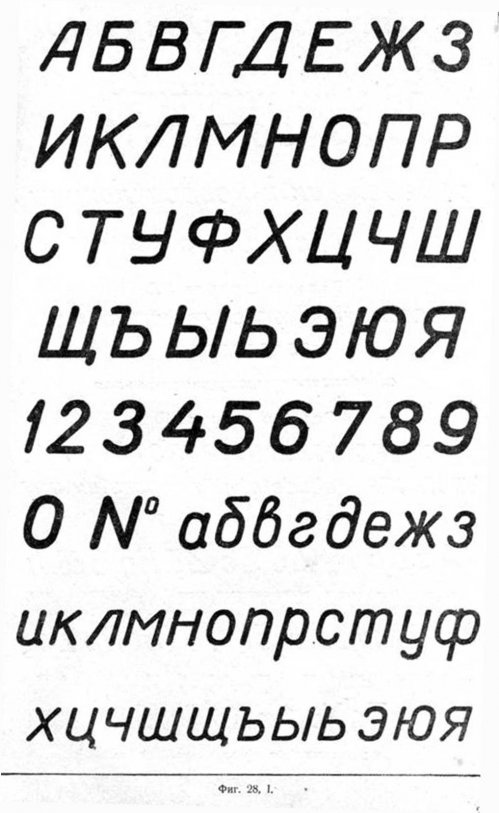
На следующем фото я выделил эти строки простым шрифтом:
Подход очень похож на тот, что я выучил в школе.
Отдельные движения точно согласованы друг с другом для создания наилучшего возможного потока письма. Только с «9» я выбрал другое управление линиями, которое поможет вам в написании кистью.
Написание чисел с помощью кистей
Типичные контрасты ширины линий, которые делают надписи кистью такими особенными, также можно применить к цифрам (для этого вам понадобится кисть).
Чтобы работать в нужных местах с большим и небольшим нажимом, важно знать основные штрихи линии.
Потому что, если вы уже можете правильно рисовать отдельные штрихи, все, что вам нужно сделать сейчас, это применить принцип письма кистью к штрихам:
- Штрихи от сверху донизу выполняются с большим давлением , создается толстая линия
- Штрихи от снизу вверх выполняются с небольшим нажимом , в результате получается тонкая линия
Цифры, написанные от руки, подчиняются тем же правилам, что и буквы.
В моей рабочей тетради по написанию кистью я посвятил цифрам специальную страницу. Так вы почувствуете линии и формы.
Фигурки старого стиля
На первый взгляд, так называемые фигурки старого стиля (известные также как миниатюрные фигуры) ничем не отличаются от обычных фигурок (маюскульные фигуры).
Только когда вы смотрите на числа в базовой системе, они раскрывают свой эффект. Точно так же, как буквы, цифры в старом стиле имеют фиксированные надстрочные и нисходящие элементы!
В результате эти цифры лучше вписываются в непрерывный текст. Для вас, как художника, они также предлагают захватывающий визуальный эффект.
В соответствии с имеющейся у вас художественной свободой, вы можете использовать эти цифры по мере необходимости – и таким образом изменить характер вашей надписи.
Разные стили
Помимо простых цифр с одинаковой толщиной линии и варианта с кистью, есть бесконечные возможности для рисования цифр от руки.
Здесь также стоит обратить внимание на различные стили рукописного письма и алфавиты.
Отдельные стили обычно прекрасно переносятся в числа.
Мощный и трехмерный, тонкий и украшенный или очаровательно декорированный – нет предела вашему воображению.
В идеале вы адаптируете внешний вид к содержанию. Это приводит к гармоничной общей работе.
Этим я бы сказал: получайте удовольствие от написания открыток на день рождения от руки!
Тимо Страус
Увлеченный художник леттеринга, дизайнер и основатель lettering.org
Тимо страстный художник леттеринга из Германии. Он любит создавать надписи и учит других делать то же самое. Кроме того, Тимо разработал несколько инструментов, чтобы новичкам было проще создавать свои первые удивительные произведения искусства.
Подробнее о Тимо Страусе
Писать буквы и цифры? – Нужна помощь? Мы здесь.
ульвен 1
Привет, можно ли как-нибудь вставить буквы в свой дизайн и вычесть их, чтобы они были выгравированы на моем изделии?
трудно рисовать буквы от руки, какие-нибудь руководства/инструкции для этого?
Victor_Shapr3D 2
Привет, Ульвен, обходной путь — нарисовать буквы в приложении для рисования, таком как Concepts, Procreate, а затем импортировать эскиз в приложение в форматах DWG/DXF.
Alphabet.shapr (664 КБ)
3 нравится
Гелфин 3
@ulven
Вы можете выполнить поиск по этому форуму для «Буквы» или «Цифры».
Существует множество размеров в верхнем и нижнем регистре.
Многие из них были созданы с использованием S3D, последний мультиталантлив.
Если вы можете делать наброски в S3D, вы можете создавать надписи в S3D.
Многие базовые схемы некоторых Букв можно легко адаптировать к нескольким другим Буквам.
Если попрактиковаться, на создание всего алфавита уйдет всего 10 минут или около того.
Если вам нужно всего несколько разных букв, то это определенно то, что вам нужно.
Совет: сетка — ваш друг, начните с БОЛЬШОГО и уменьшите масштаб до нужного вам размера.
Счастливый S3Ding.